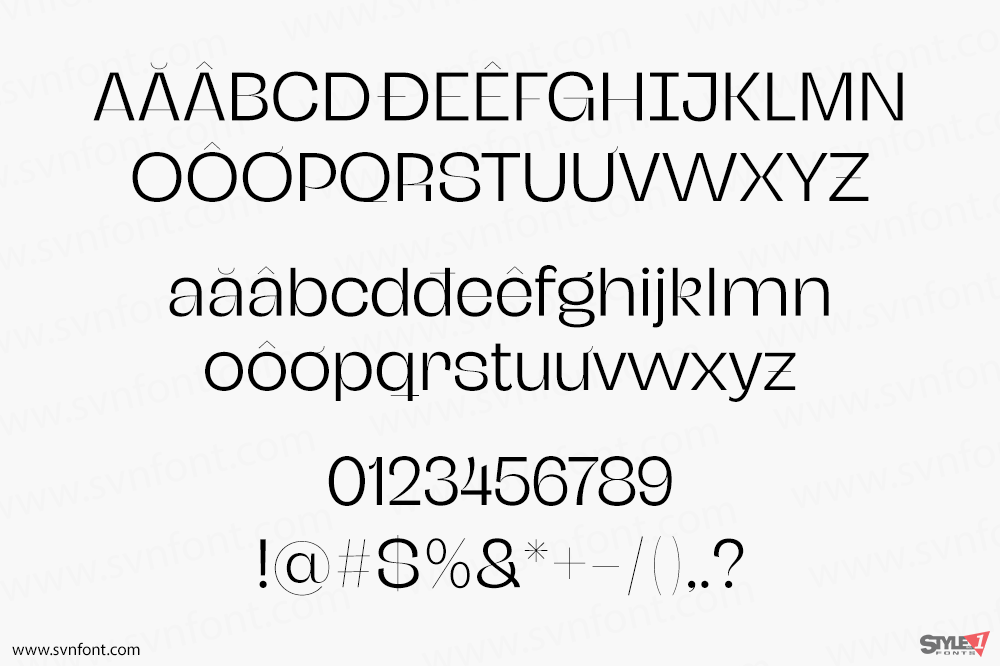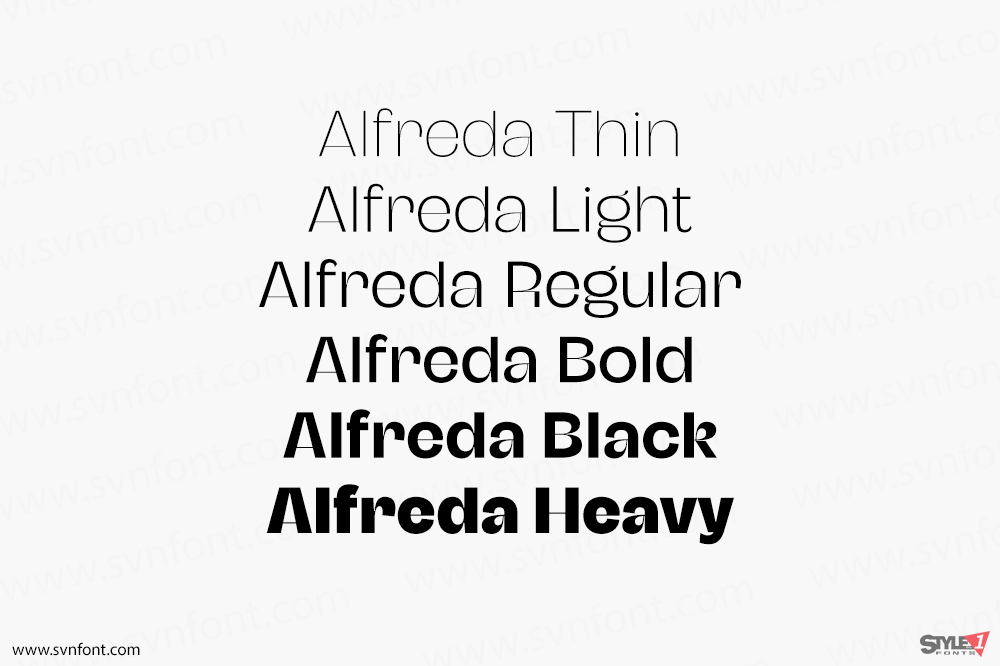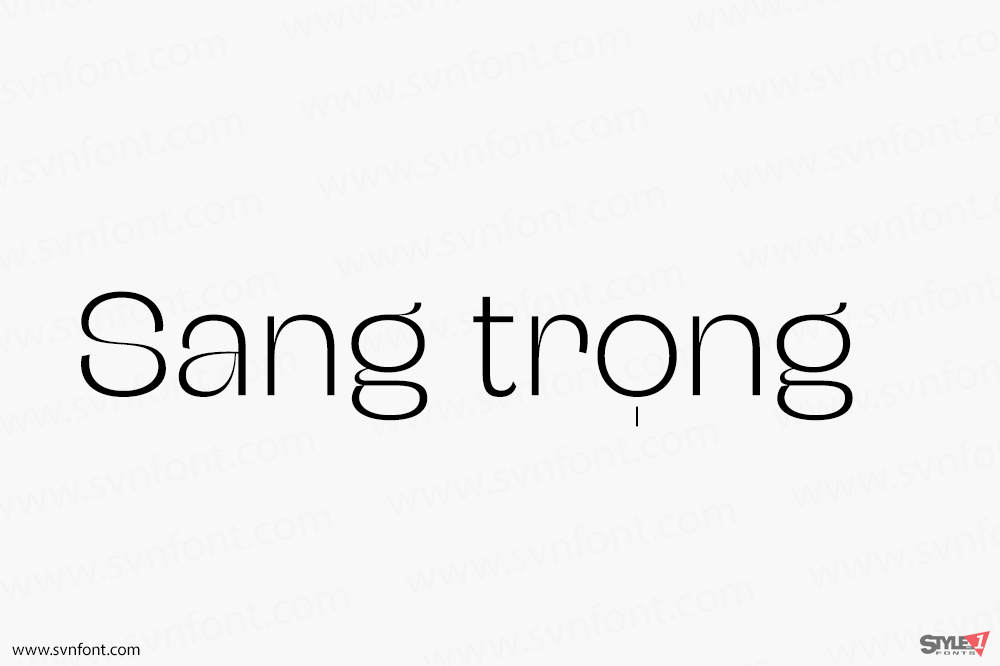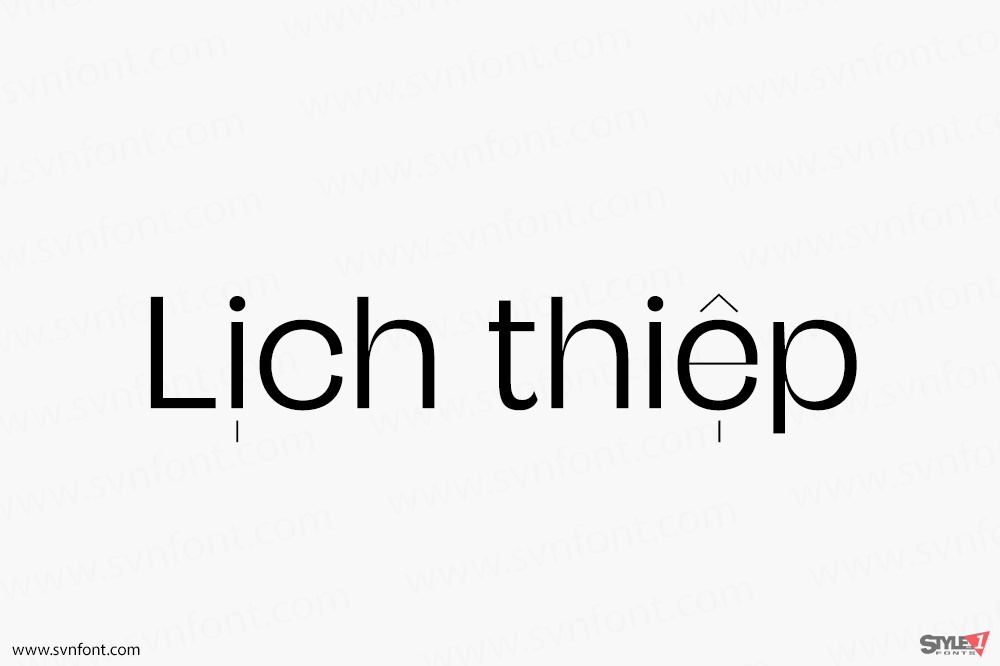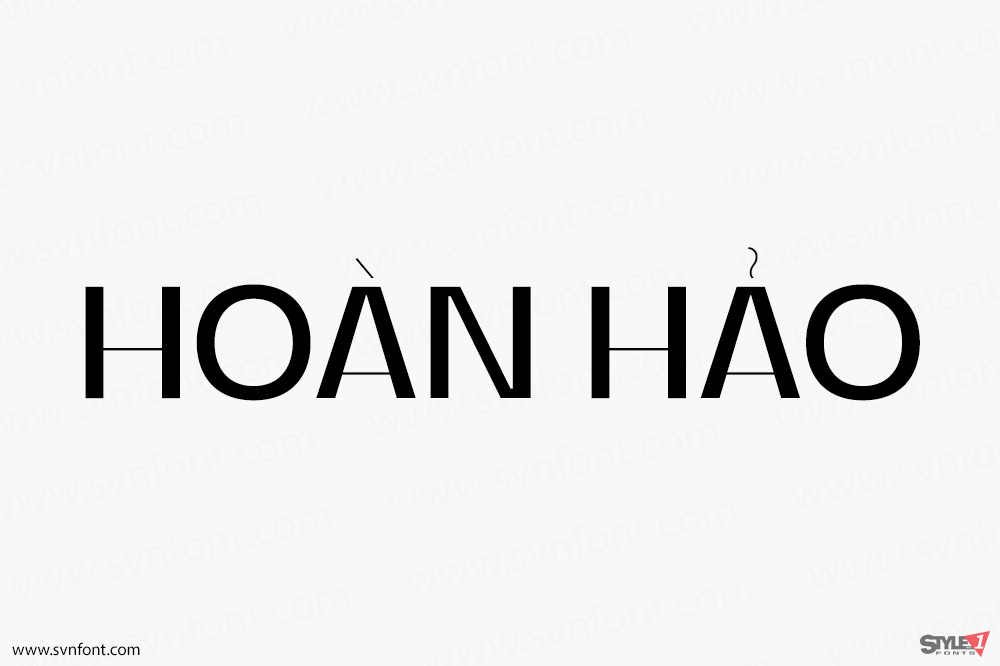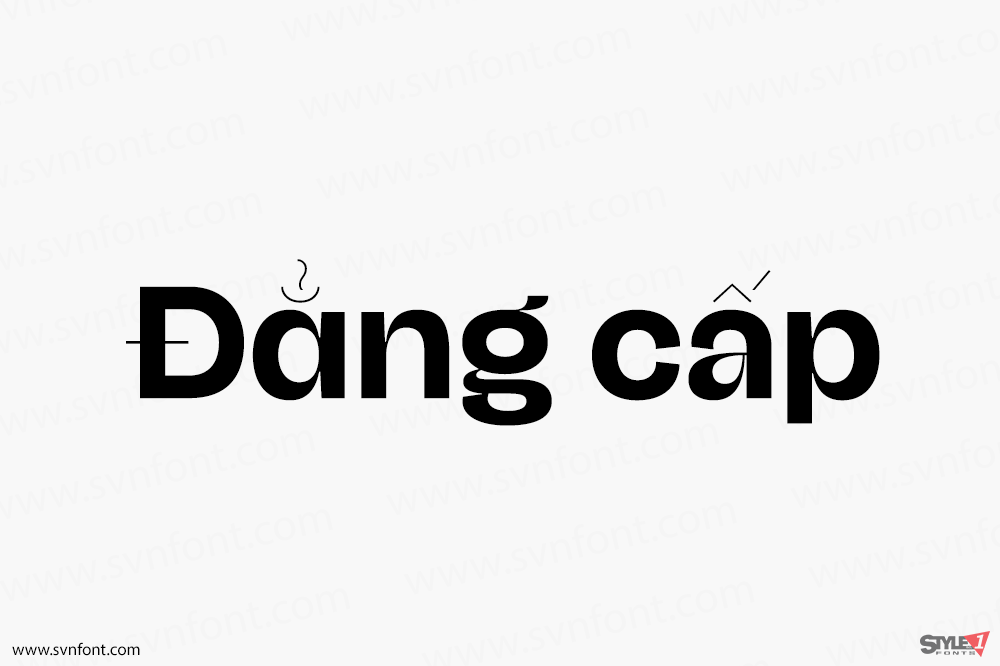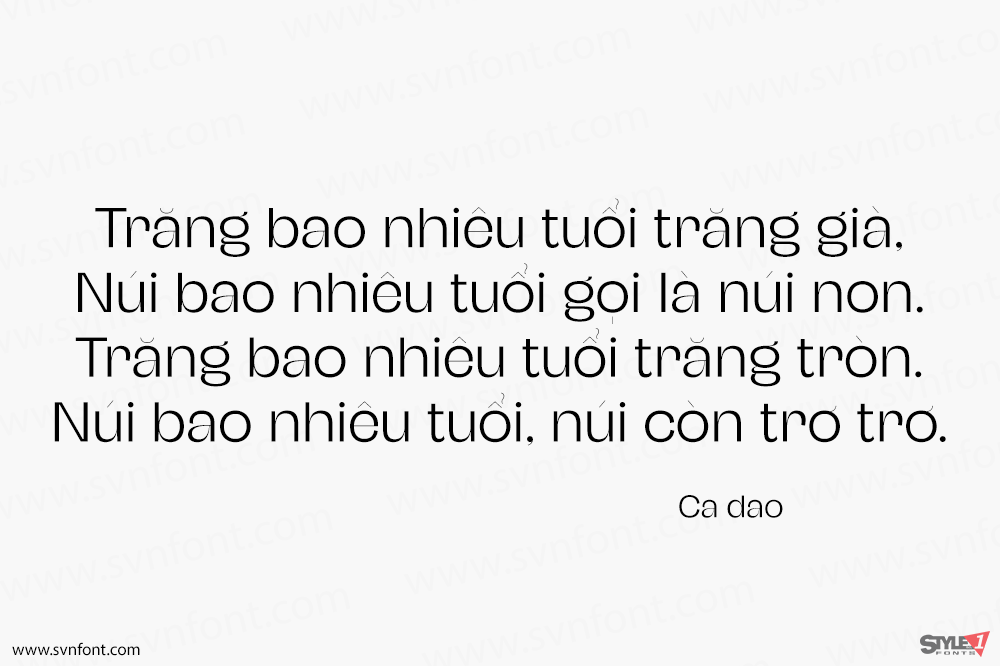
Alfreda Grotesque không chỉ là một kiểu chữ grotesque thông thường. Hình thái của nó pha trộn giữa các nét đậm nhạt và không đậm nhạt, cùng với độ tương phản tự nhiên và đảo ngược. Tất cả những điều đó được kết hợp với một chút cảm hứng nhân văn và các rãnh mực (ink traps) tinh tế. Thật độc đáo. Alfreda có 6 độ đậm, sở hữu các tính năng OpenType, hơn 400 glyph và 18 bộ kiểu cách (stylistic sets).
Nhà thiết kế: Santi Rey
Nhà phát hành: Santi Rey